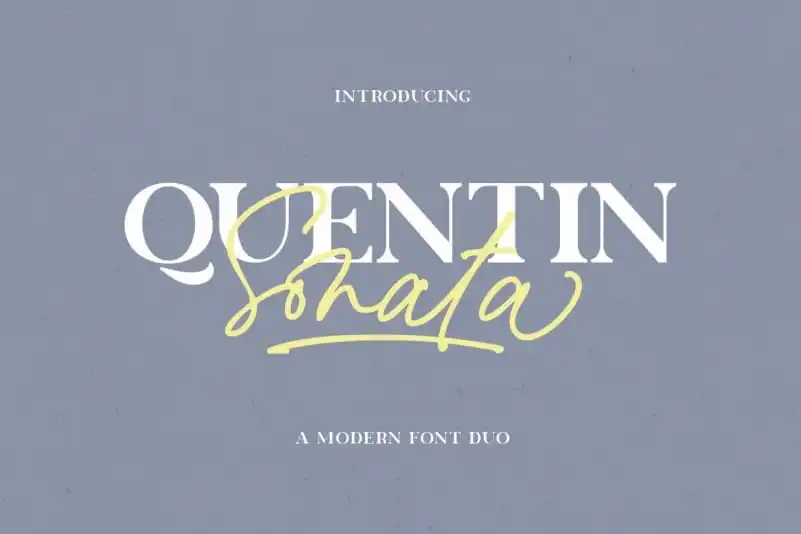
A fonte ‘Quentin Sonata Handwritten Font’ é uma criação delicada e meticulosamente desenhada pela Rillatype no formato de letra cursiva. Esta elegante fonte, que cativou os olhos dos designers na plataforma 99designs, oferece um toque suave e bem equilibrado aos seus caracteres. Suas letras proporcionam uma experiência visual única e sofisticada perfeita para projetos que requerem um toque de elegância, como a criação de marcas ou logomarcas, embalagens de produtos, headlines ou frases marcantes. Com sua versatilidade impressionante, Quentin Sonata é capaz de dar vida a uma variedade de trabalhos gráficos, desde o branding até as mais elaboradas peças de design. Sua natureza elegante e bem equilibrada torna-a uma escolha ideal para aqueles que desejam adicionar um toque especial ao seu trabalho visual. Seja em letras grandes ou menores, a fonte ‘Quentin Sonata Handwritten’ traz uma autenticidade única à sua criação, oferecendo sempre um acabamento de alta qualidade e beleza.